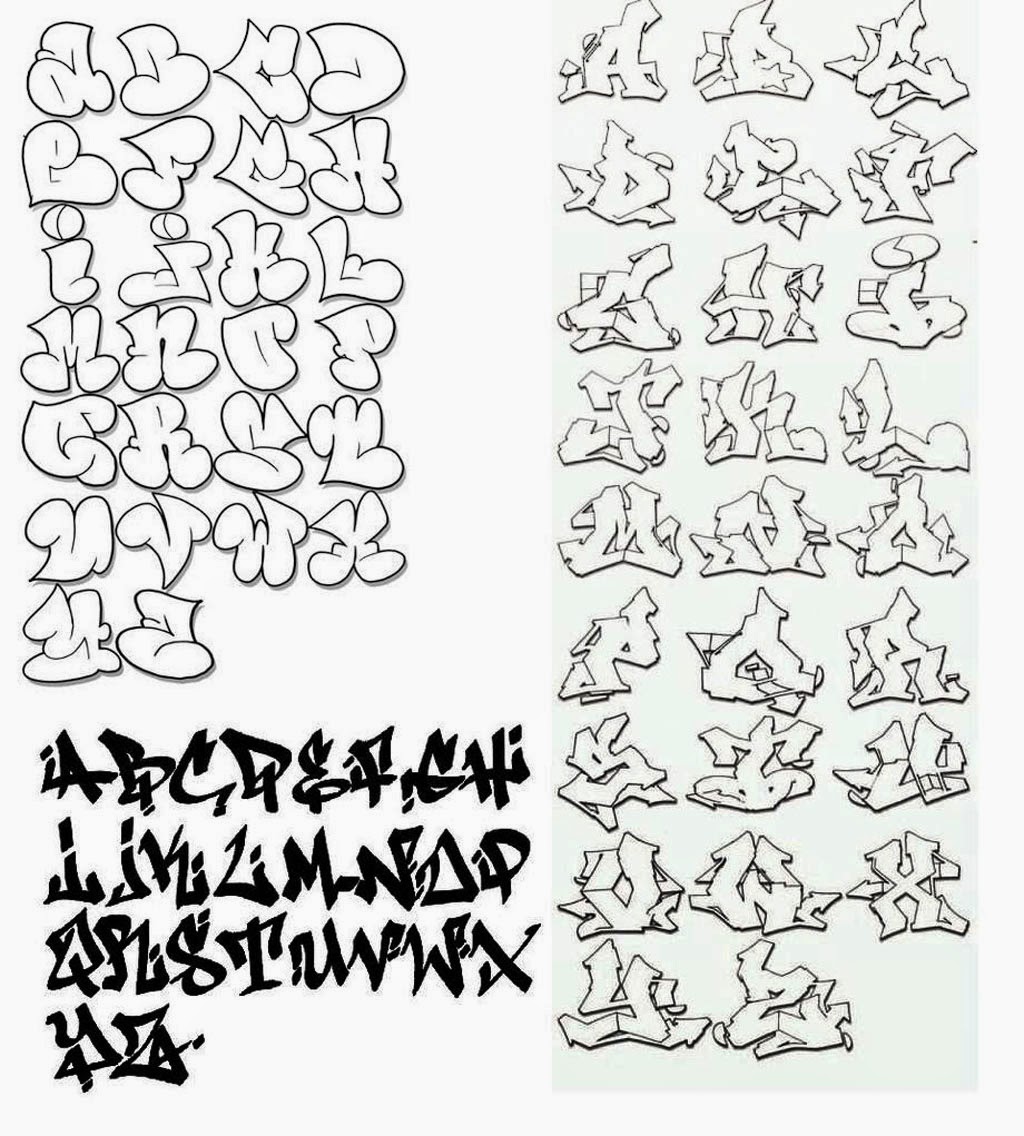
Подборка граффити шрифтов для проектов
Теперь вы увидите работы, вдохновленные уличным искусством, которые охватывают все, от рекламы до оформления альбомов. Рост популярности означает, что в ваших проектах есть множество тематических граффити-шрифтов. С формами от спрей-покраски и брызг до надписей кистью и стилей трафарета, мы получили все это.
В этом посте мы собрали лучший граффити-шрифт, который только можно найти в Интернете, но если вы ищете другой тип шрифта, почему бы не проверить наш пост о бесплатных шрифтах? Или вы можете продолжить городскую атмосферу и исследовать наш выбор уличного искусства.
Metro Grunge
Metro Grunge — бесплатный шрифт от Peter Olexa, независимого дизайнера из Братиславы, Словакия. Шипение энергии подполья (как метафорического, так и актуального), этот шрифт бесплатный как для личного, так и для коммерческого использования.
Extreme Travel
Extreme Travel Font — это шероховатый шрифт в стиле граффити, созданный колумбийским графическим дизайнером и иллюстратором Луисом Харамильо. Он имеет изобретательный вид, который в основном состоит из белых букв, нанесенных трафаретом из брызг, окрашенных брызгами. Этот демонстрационный шрифт доступен для бесплатной загрузки только для личного использования.
Flow
Созданный болгарским дизайнером Десси Давидовой, Flow «вдохновлен неровностями». Кажется, что он легко находит место между элегантным и вольным стилем, что делает его хорошо подходящим для граффити-проектов.
Broken Wings
Broken Wings — это зубчатая, нервирующая гарнитура от Bdstrd Std, которая включает в себя большие и маленькие буквы, а также стандартные цифры и символы.
Vitruvian Man
Этот шрифт дикий, дикий, дикий: если вы хотите обратить внимание на злобную, вандалистическую сторону граффити-культуры, Витрувианский Человек вполне может быть отличным выбором. Разработанный Checkered Ink, этот шрифт бесплатный только для личного использования.
Youth Fury
Нужно вспомнить оригинальный стиль вандализма граффити? Точно названная Молодежная Ярость вызывает дух недовольной молодежи. Работает колумбийский графический дизайнер и иллюстратор Луис Харамильо, его можно бесплатно скачать только для личного использования.
Sister Spray
Получите беспорядок с этим фантастически грубым и готовым шрифтом, снова от ImageX. Он состоит из полного набора букв в верхнем регистре, окрашенных распылением, а также нескольких строчных букв для выделения, а также брызг, брызг и ударов, чтобы завершить внешний вид. Это бесплатно для личного использования.
The Fresh Prince
Первый шрифт от Team Knorke, The Fresh Prince, дизайн граффити — один из наших любимых. «У нас была идея для этого после некоторого пива и обсуждения о шутливости большинства граффити-шрифтов», — заявляет член команды Феликс Шварце на Behance. «Мы набросали буквы довольно грязные с помощью стандартного фломастера — уличного стиля».
Gang Bang Crime
Дизайнер Maelle Keita — еще один шрифт с полностью заглавными буквами — предлагает два набора, один с другим, а другой без капающей краски Этот шрифт бесплатный только для личного использования.